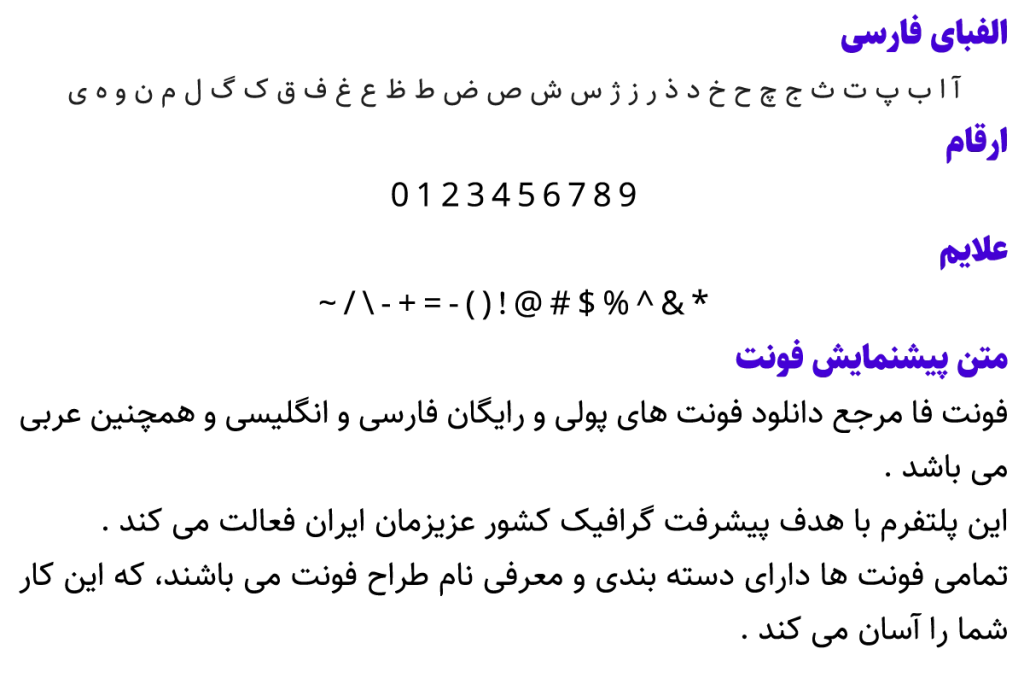
فونت فارسی ساحل - Sahel
توضیحات و معرفی فونت ساحل
فونت فارسی ساحل ( Sahel ) از مجموعه فونت های آزاد و برتر می باشد، همچنین نوع فونت طراحی وب و عنوان و متن می باشد.
فونت فوق العاده زیبای معرفی شده توسط صابر راستی کردار در سال 1398 طراحی و ساخته شده است.
همچنین فونت ساحل در 5 وزن سبک و معمولی و نیمه پر رنگ و سنگین است.
در لیست زیر می توانید وزن های این فونت فوق العاده زیبا را ببینید.
1. Sahel Light
2. Sahel Regular
3. Sahel DemiBold
4. Sahel Bold
5. Sahel Black
در تصویر زیر می توانید زیبایی این فونت با ترکیبی از شعر زیبای وطنم را ببینید و لذت ببرید.